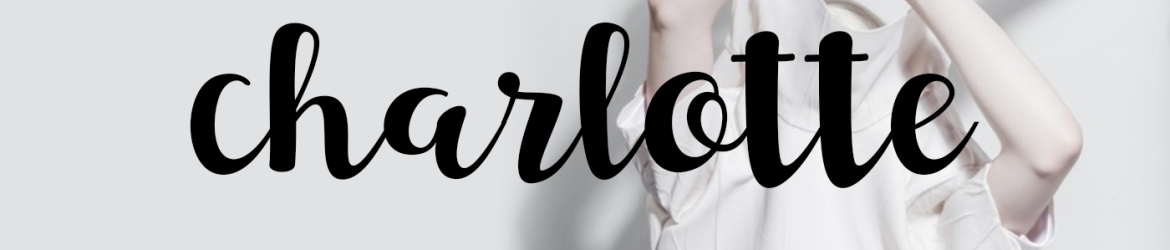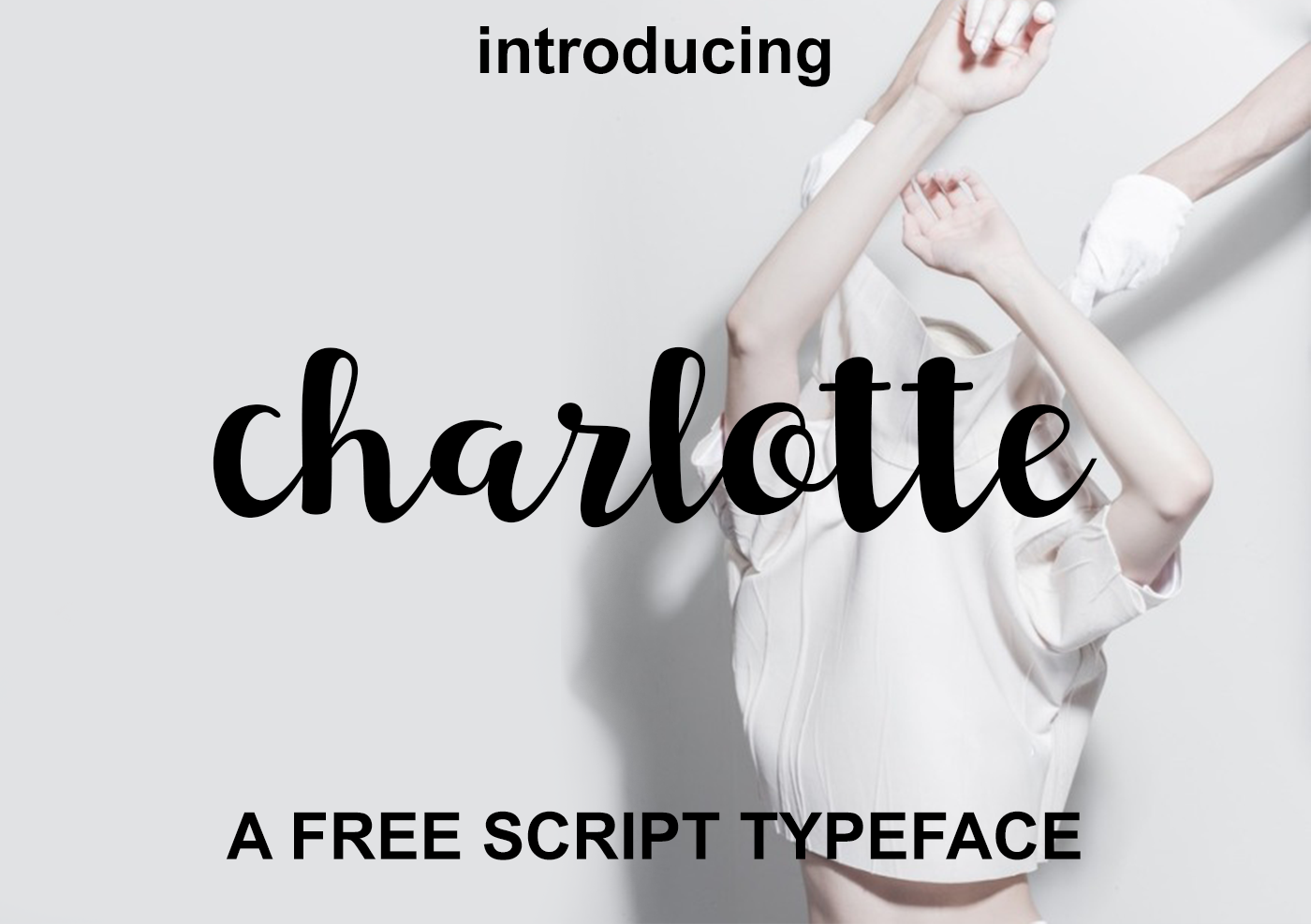
Charlotte Script Font – Fonte Grátis
Charlotte Script Font
A Charlotte Script Font é uma novidade do designer Hamilton, trazendo a elegância e charme dos traços manuscritos em uma tipografia script digitada. Este recurso de tipo, categorizado como handwritten fonts, oferece um touch suave e bouncier que se destaca para aplicações variadas – desde marcas criativas até cartões de convite festuais. Suas linhas elegantes e detalhes refinados são perfeitos para criar ambientes agradáveis em design gráfico. Seja o texto de um logotipo, as frases no layout da sua marca ou uma caixa de produto com cara de amor – a Charlotte Script Font é versátil o suficiente para capturar qualquer momento especial que você possa imaginar. Com seu formato digitalizado, essa fonte permite que você transforme seu design em algo único e memorável. Não deixe de experimentar esta fonte elegante no seu próximo projeto!